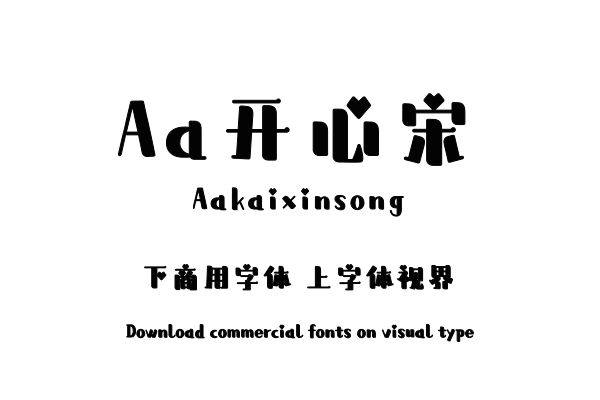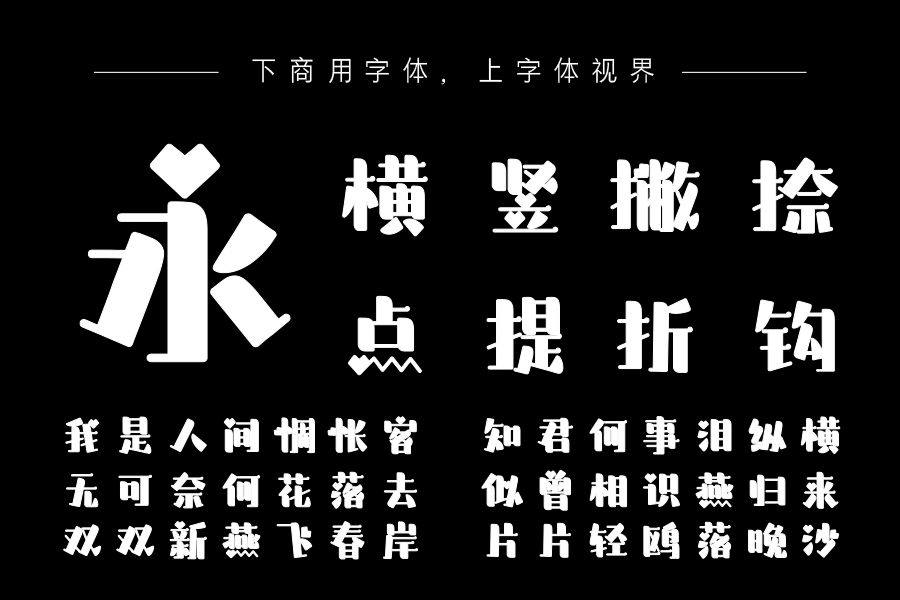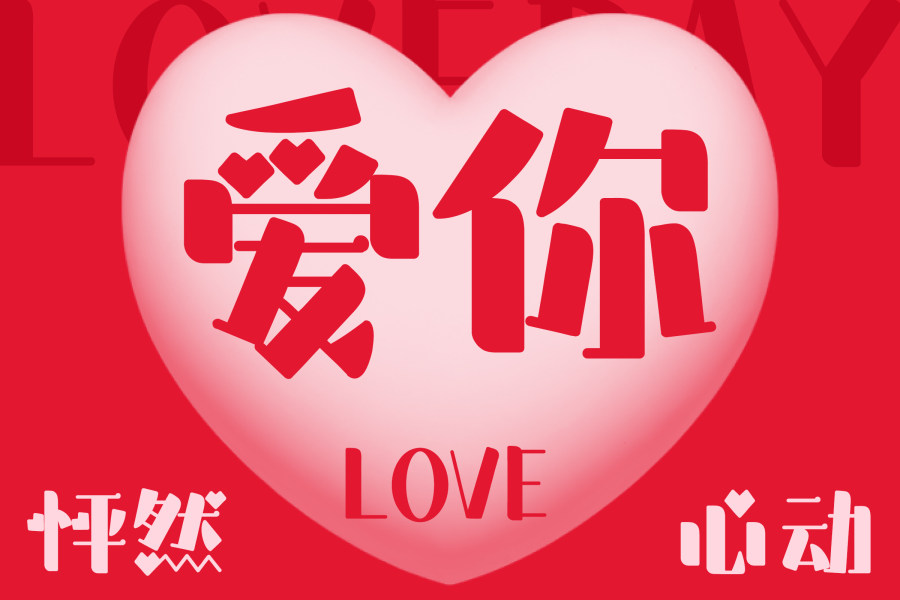
手绘的字形,跳跃的结构,笔画横细竖粗形成强烈的对比。点笔画替换为爱心为该字体平添了几分俏皮可爱,轻松,舒适又有趣。适用于儿童类品牌广告的设计。购买须知:“下载服务费”与“字体VIP”所获得字体 仅用于个人非商用, 商用请联系付费授权。本字体为电脑用字,手机没有root权限不支持直接手机换字(手机如何root,请自行百度搜索教程)。购买前请先 了解清楚后再付款 ,字体为虚拟产品无法回收 一旦购买不支持退款。